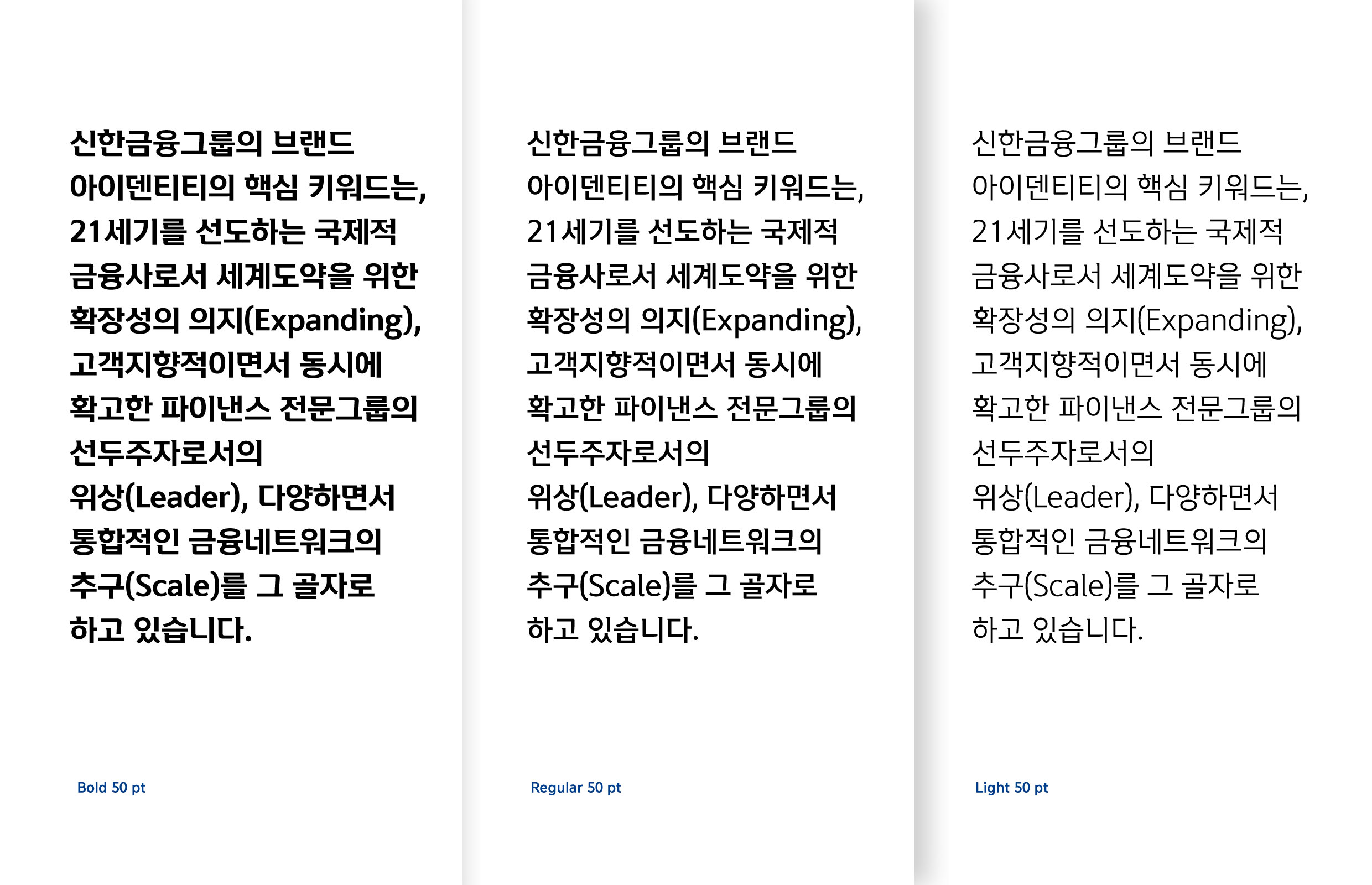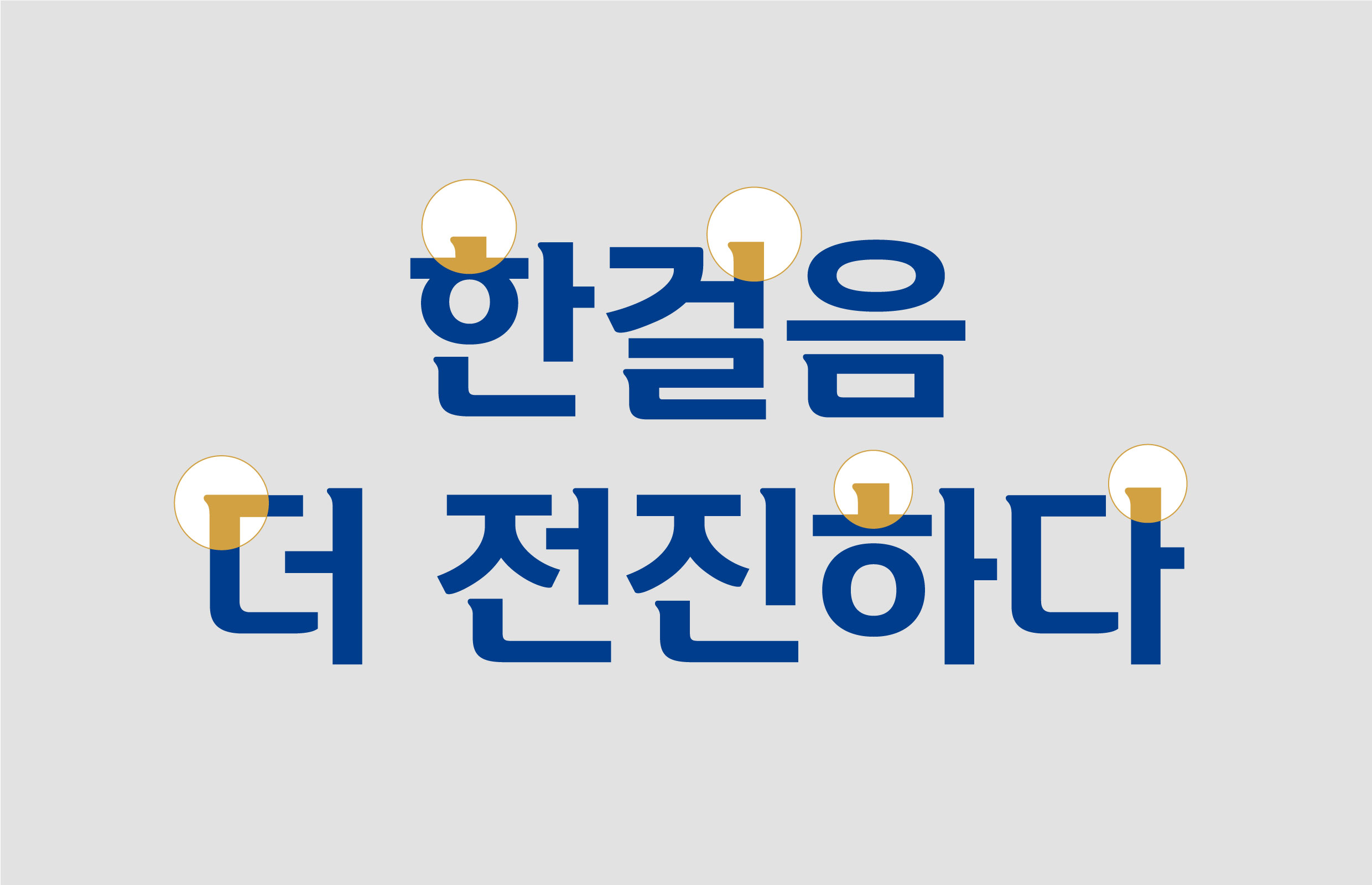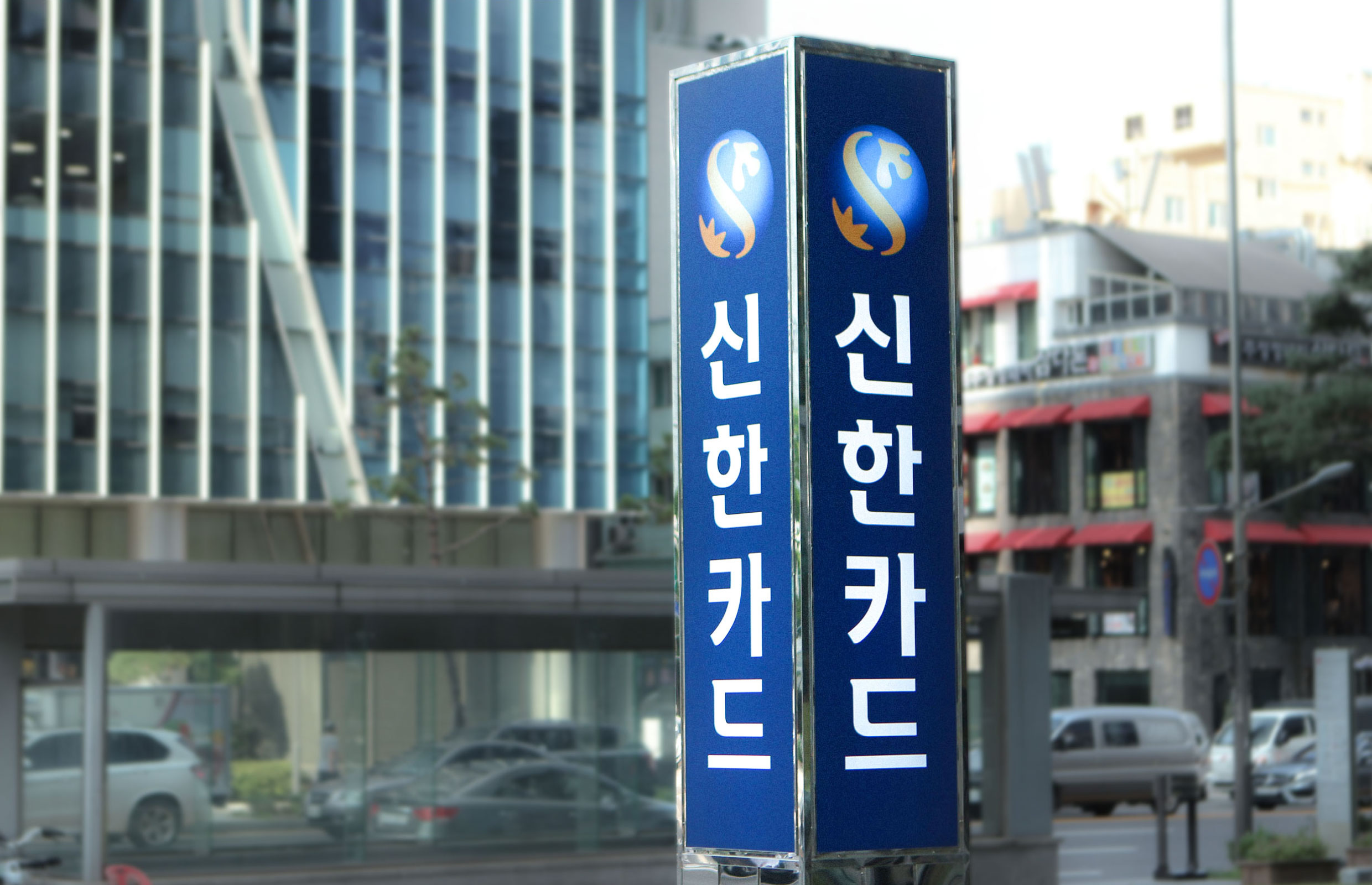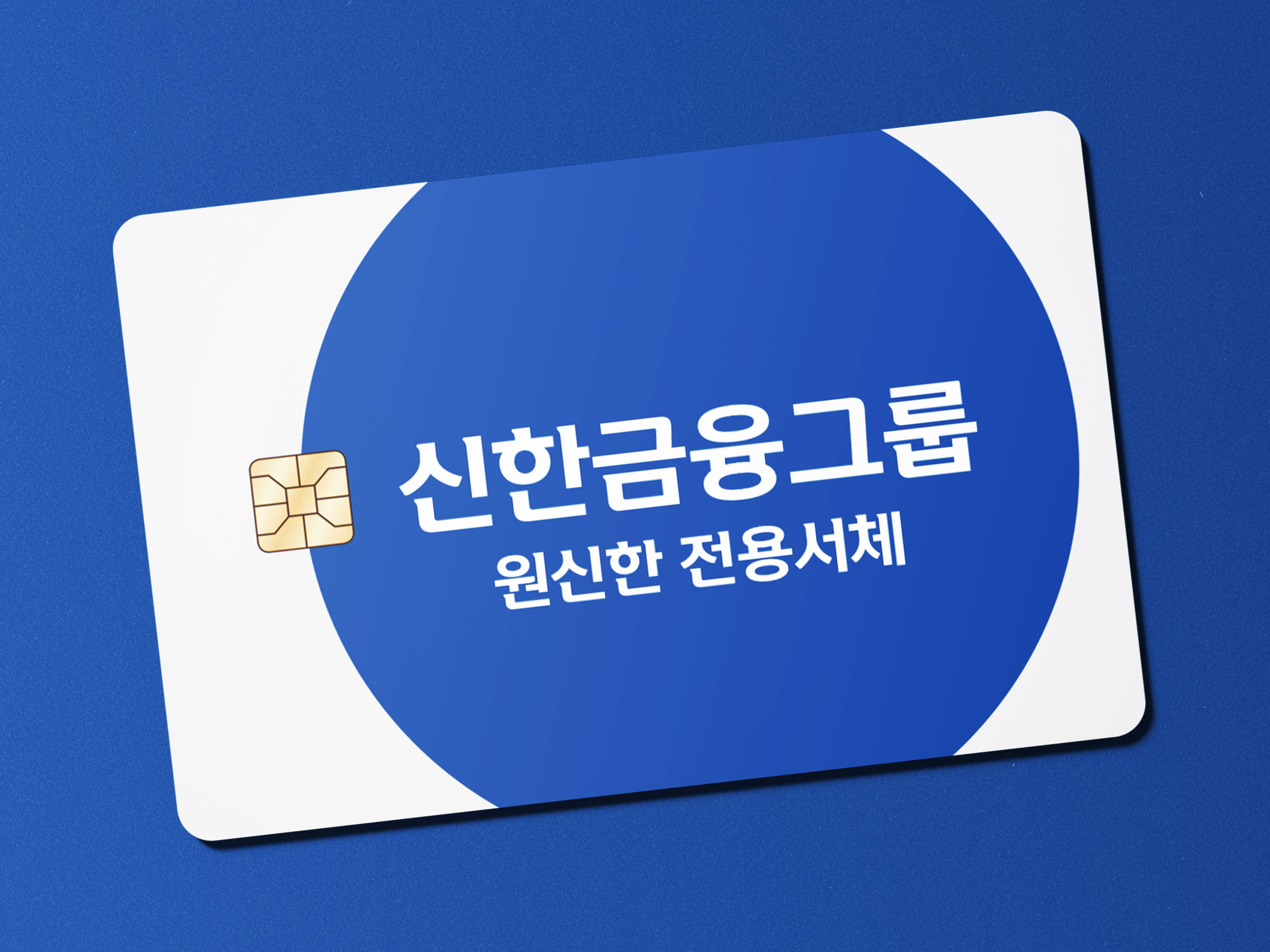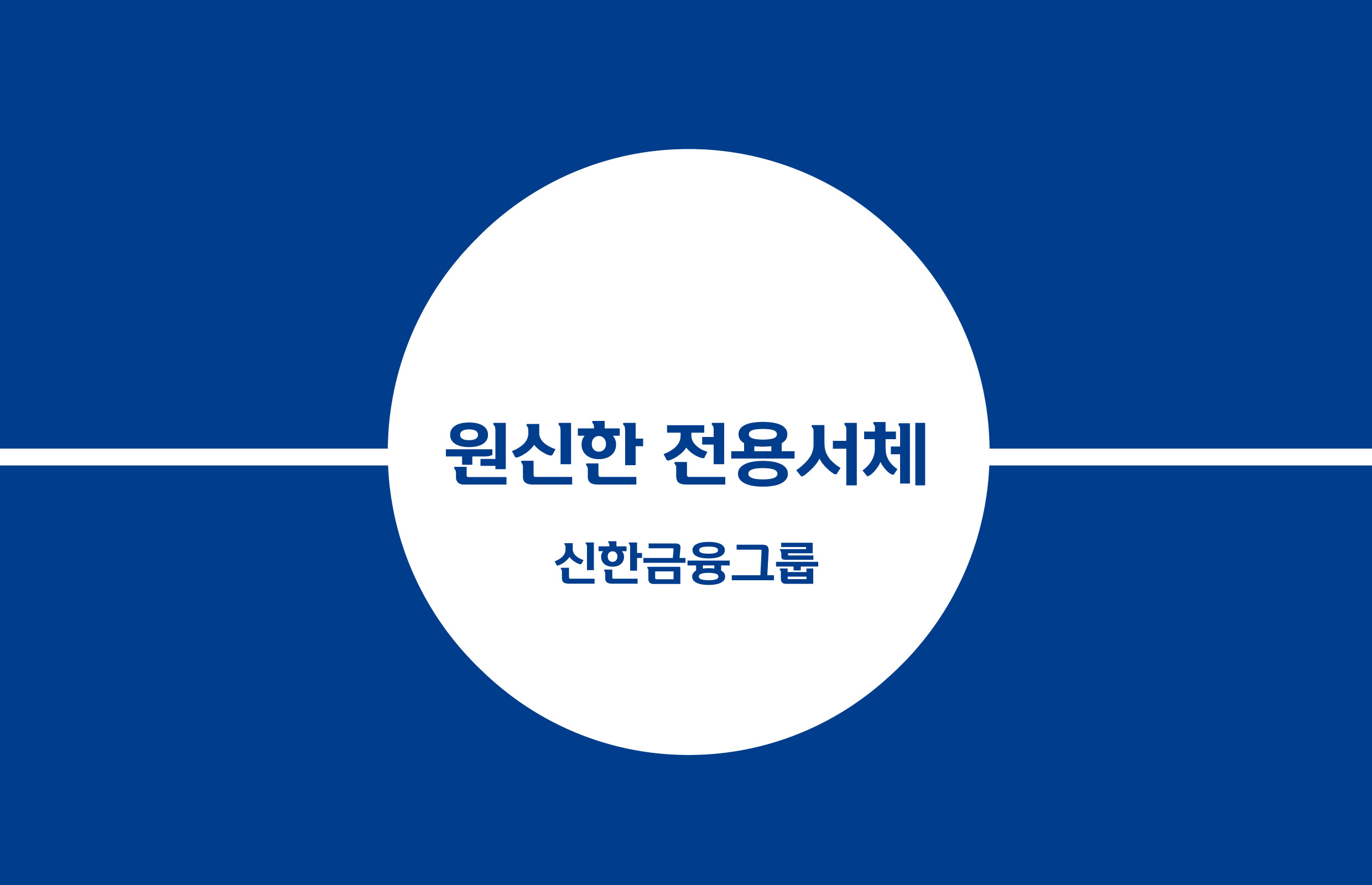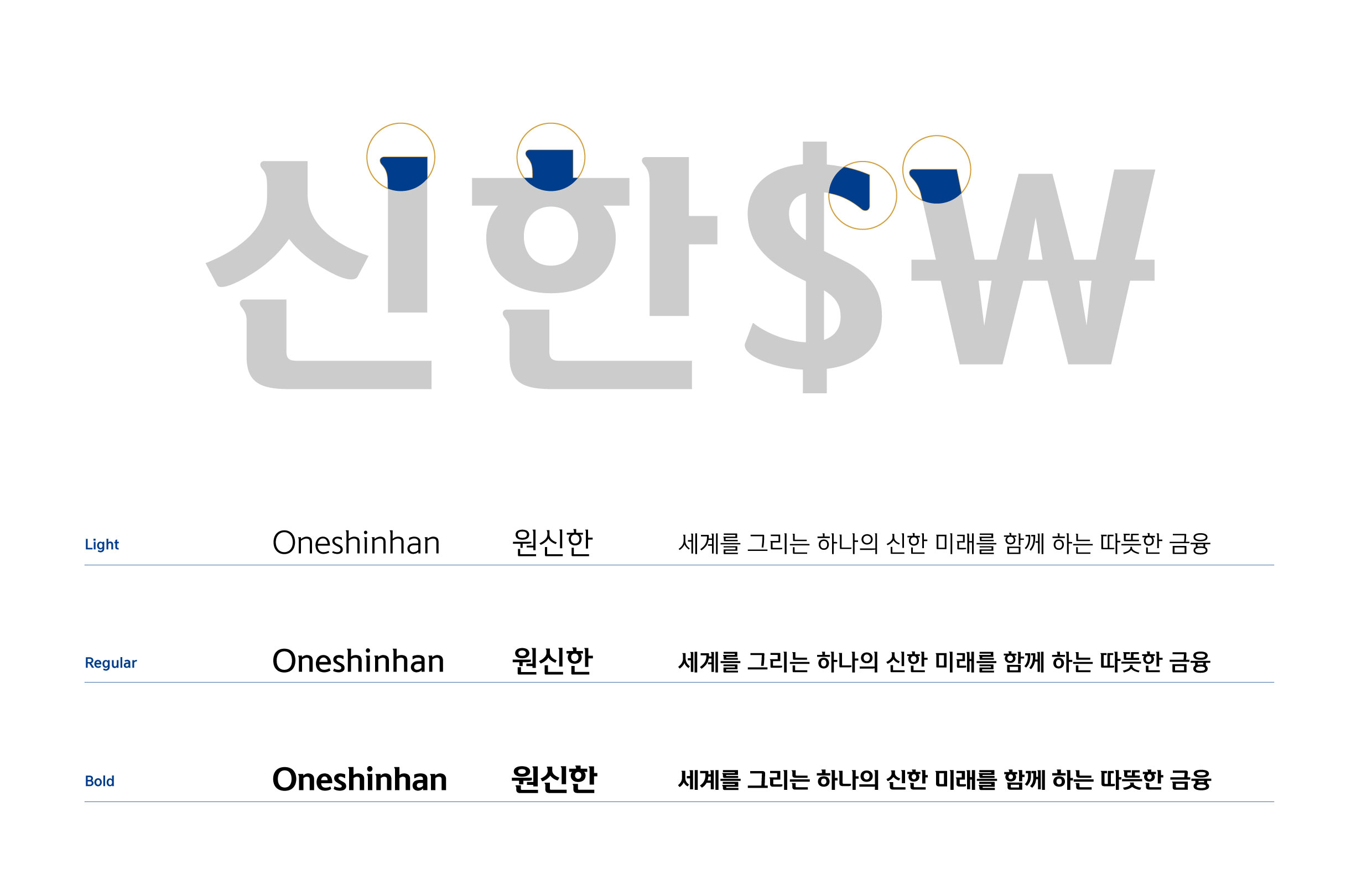
신한금융그룹
신한금융그룹 [원신한체]
‘원(One)신한’ 서체는 2016년 발표된 라틴 알파벳 서체와 조응하는 한글 서체다. 국내외 금융 리더로 도약하는 신한금융그룹의 모던한 이미지를 표현했으며, 모바일 환경 사용성을 높이기 위해 라이트(Light) 서체에는 힌팅(hinting)을 적용했다.